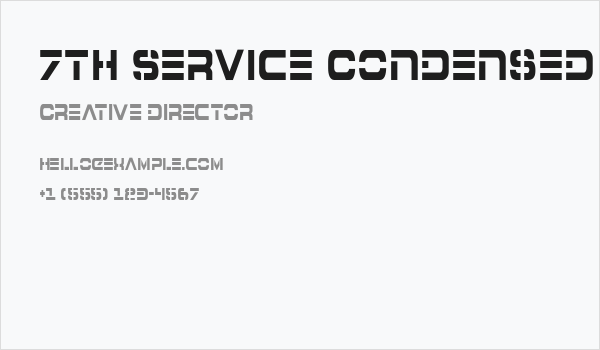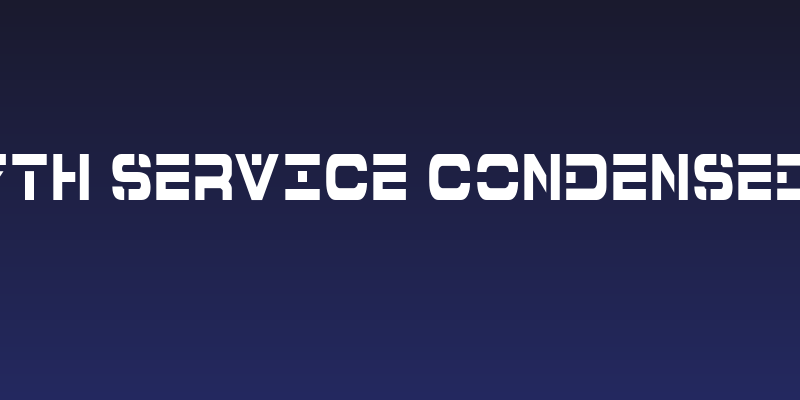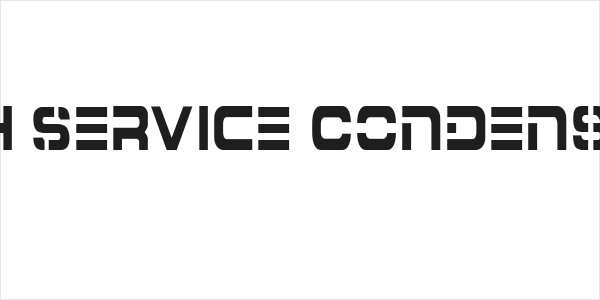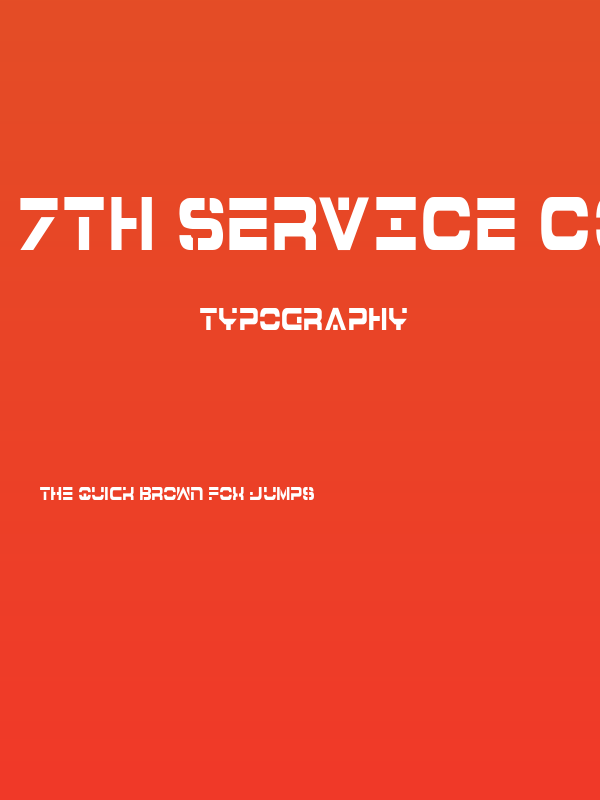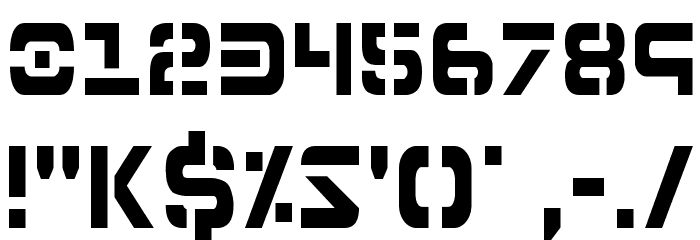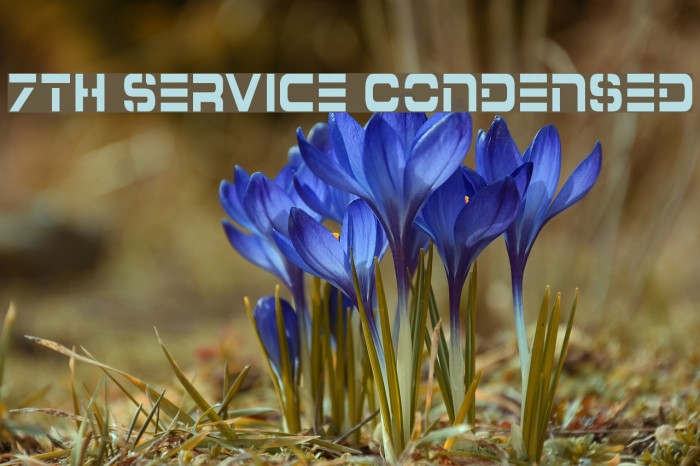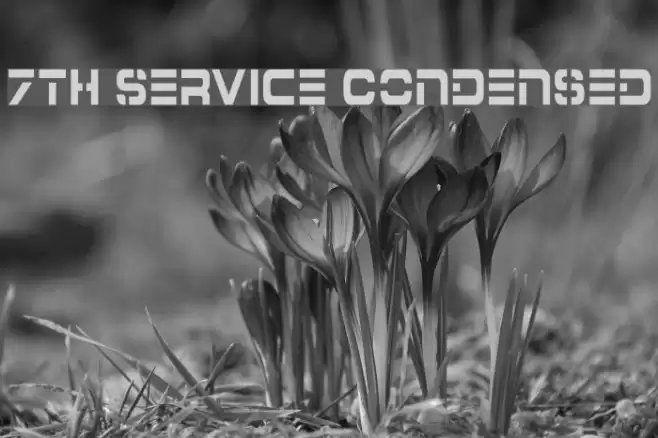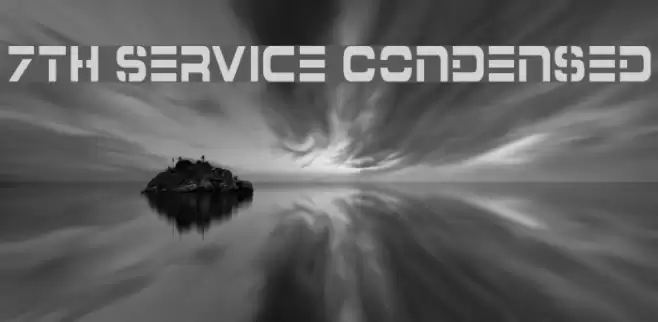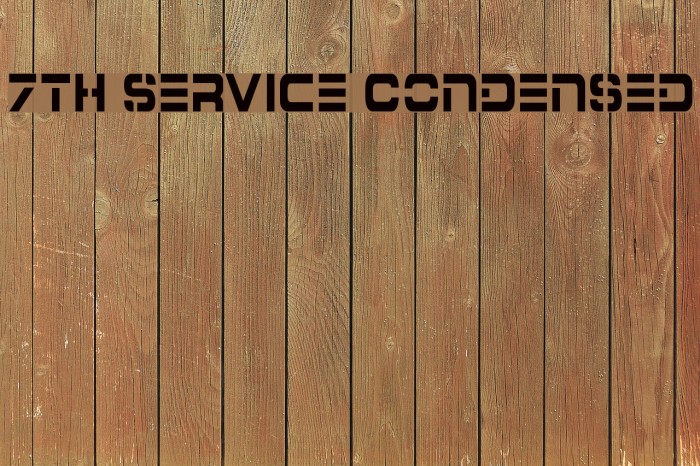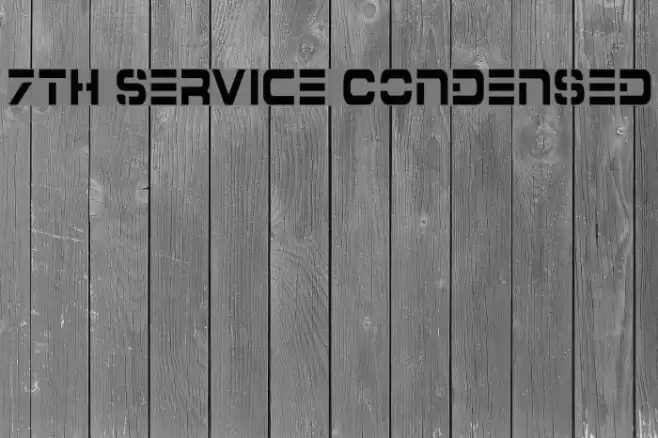
7th Service Condensed Font
| Vorgeschlagene Projekte | Ideal for use in technology branding, futuristic posters, industrial-themed designs, and bold headlines. |